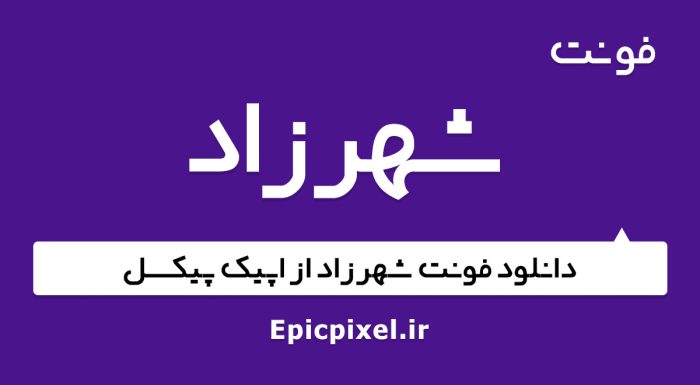
فونت شهرزاد فارسی Shahrzad
دنیای طراحی گرافیک به فونت هایی نیاز دارد که هم زیبا باشند و هم کارآمد، قلم هایی که بتوانند در عین داشتن هویت بصری متمایز، در کاربردهای متنوعی به خوبی بدرخشند. فونت فارسی شهرزاد، اثری از جناب هاشم شهرزاد، طراح خلاق و خوش ذوق ایرانی، یکی از این فونت ها است که با رویکردی خاص طراحی و اجرا شده است. این قلم با ساختاری که در عین سادگی، خاص و متفاوت است، خروجی بسیار یکدست و زیبایی ارائه می دهد.
فونت شهرزاد یک فونت حرفه ای است که زیبایی خود را مدیون سادگی حساب شده و متفاوتش است. عناصری که در طراحی این فونت به کار رفته اند، به گونه ای در کنار هم قرار گرفته اند که نتیجه نهایی بسیار یکدست و زیبا است و آن را به گزینه ای مناسب برای طراحی های بصری تبدیل می کند.
این فونت زیبا توسط شخص هاشم شهرزاد طراحی و ساخته شده و حاصل کار یک طراح قلم باتجربه است. هرچند در توصیف این فونت گاهی از واژه “فانتزی” استفاده شده، اما سادگی و یکدستی ساختار آن باعث شده است که کاربردش از طراحی های صرفاً فانتزی فراتر رفته و در زمینه های بسیار گسترده تری به خوبی عمل کند، همان طور که در نمونه های تایپ شده آن مشهود است.
فونت شهرزاد با فرمت استاندارد ttf ارائه می شود که بالاترین سازگاری را با نرم افزارهای مختلف دارد. این فونت تنها دارای یک وزن Bold می باشد، اما همین یک وزن به واسطه طراحی قوی، قابلیت های فراوانی را پوشش می دهد. از نظر پشتیبانی زبانی، این فونت از زبان فارسی به طور کامل پشتیبانی می کند و شامل اعداد فارسی نیز می شود که آن را برای استفاده در محتوای فارسی کاملاً مناسب می سازد. کیفیت مناسب و بالای این فونت نیز از دیگر مزایای آن است.
یکی از نقاط قوت برجسته فونت شهرزاد، versatility یا گستره کاربرد بالای آن است. این فونت تنها مناسب طراحی های خاص یا نمایشی نیست، بلکه به طور ویژه برای تایپوگرافی و نوشته های طولانی نیز دسته بندی می شود. این ویژگی، شهرزاد را از بسیاری فونت های صرفاً عنوانی یا تزئینی متمایز می کند و آن را برای طراحی کتاب ها، مجلات و متون بلند که نیاز به خوانایی در کنار زیبایی دارند، مناسب می سازد.
علاوه بر متون طولانی، فونت شهرزاد مناسب انواع طراحی گرافیکی است و محدودیتی در استفاده از این فونت در کارهای مختلف وجود ندارد. از آن می توان در طراحی بنرها، پوسترها، جلد کتاب، لوگوتایپ های مدرن، اینفوگرافی ها، کارت ویزیت و تراکت و پوستر استفاده کرد. زیبایی این فونت باعث شده تا در تمام این زمینه ها به خوبی خود را نشان دهد. مزیت خرید این فونت، دریافت آپدیت های بعدی فونت به صورت رایگان است که تضمین کننده به روز بودن شماست.
در نهایت، فونت شهرزاد با طراحی ساده اما خاص و حرفه ای خود، پشتیبانی کامل از زبان فارسی، ارائه در یک وزن کاربردی Regular و مناسب بودن برای طیف وسیعی از کاربردها از متون طولانی تا لوگوتایپ، یک گزینه Premium ارزشمند برای طراحانی است که به دنبال کیفیت و زیبایی در کارهای خود هستند و با تهیه قانونی آن، از زحمات طراح نیز حمایت می کنند.